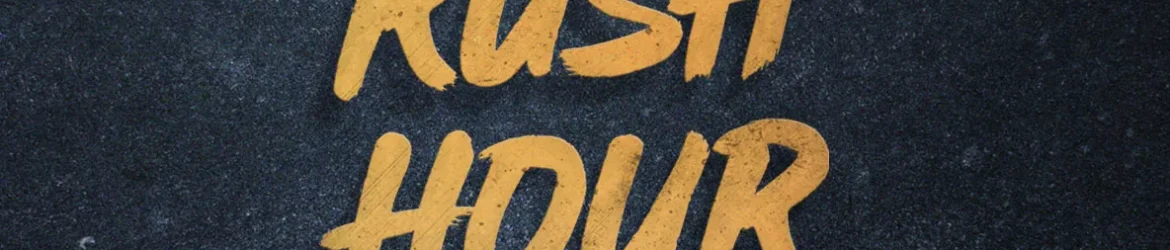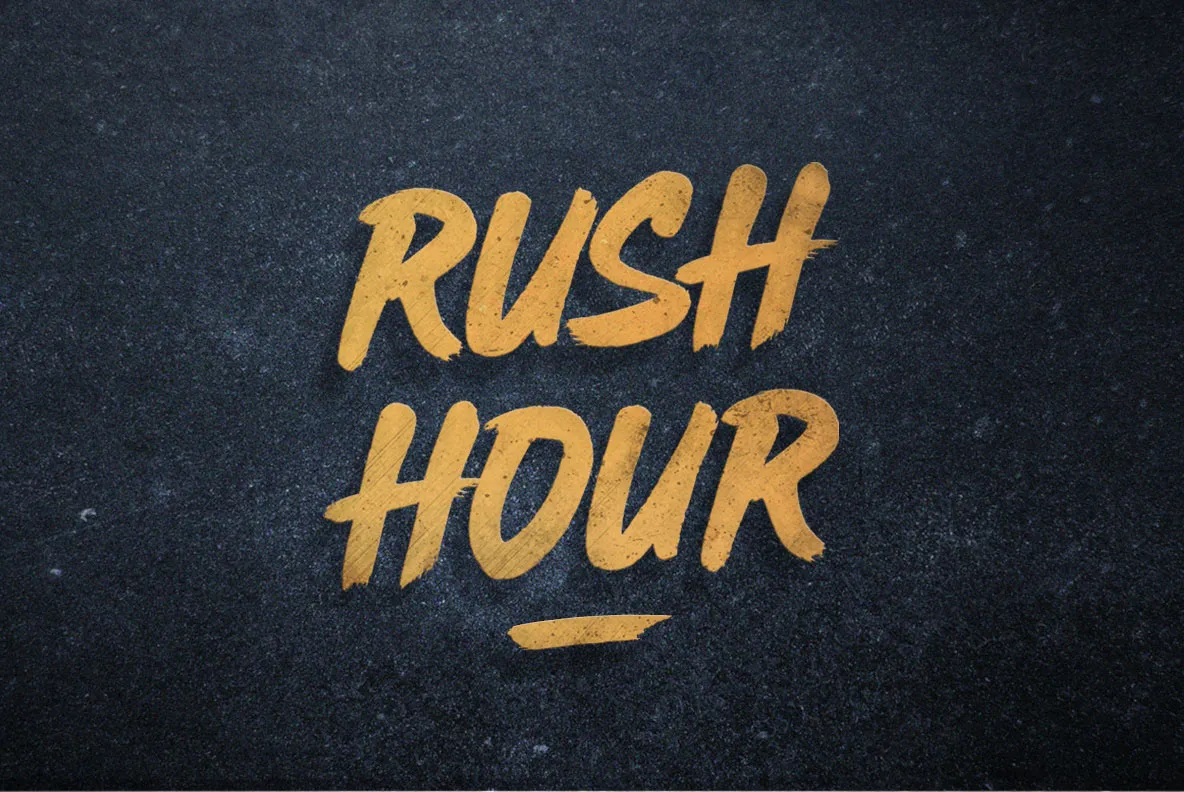
Rush Hour Brush Font – Fonte Grátis
Rush Hour Brush Font
Rush Hour Brush Font é uma elegante escolha para projetos que valorizam a mão-de-obra artesanal e a delicadeza do design manual. Criada por 178-MC, esta fonte script foi produzida com um pincel e tinta, oferecendo uma sensação de personalidade e criatividade nos seus projetos. Seja em cartões de aniversário, convites para casamentos, cabeçalhos de site ou materiais de marca, Rush Hour se destaca por sua riqueza em detalhes e seu charme sofisticado que o torna perfeito para qualquer projeto inovador e único. Com seu formato suave e delicado, ele certamente dará um toque especial a suas t-shirts personalizadas ou qualquer outro projeto criativo de sua escolha.